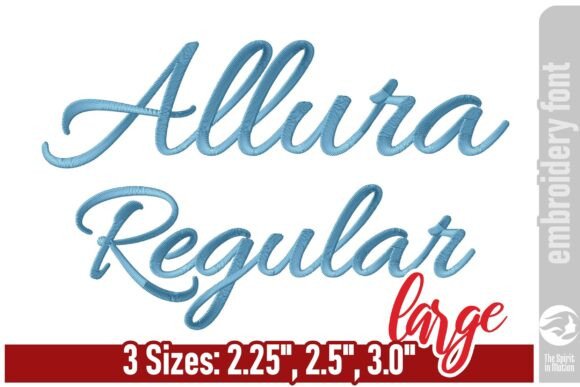
Allura Script Embroidery Font - Large
หากคุณกำลังมองหาเนื้อหาคุณภาพสูงเช่น Allura Script Embroidery Font - Large แพ็คเกจพรีเมียมนี้เป็นตัวเลือกที่ยอดเยี่ยมสำหรับโปรเจ็กต์สร้างสรรค์ของคุณ
สร้างขึ้นอย่างแม่นยำ Allura Script Embroidery Font - Large ให้เวกเตอร์ที่สะอาด พิมพ์ตัวอักษรที่ราบรื่น และใบอนุญาตเชิงพาณิชย์เพื่อความสบายใจ
✅ Pros
❌ Cons
Who Is This Best For?
ไม่ว่าคุณจะสร้างผลิตภัณฑ์ POD (Print on Demand) คำเชิญงานแต่งงาน หรือกราฟิกโซเชียลมีเดีย Allura Script Embroidery Font - Large ก็เหมาะสมอย่างยิ่ง
เคล็ดลับจากผู้เชี่ยวชาญ: รวมองค์ประกอบเหล่านี้กับฟอนต์เสริมเพื่อสร้างการออกแบบที่โดดเด่นและเป็นเอกลักษณ์